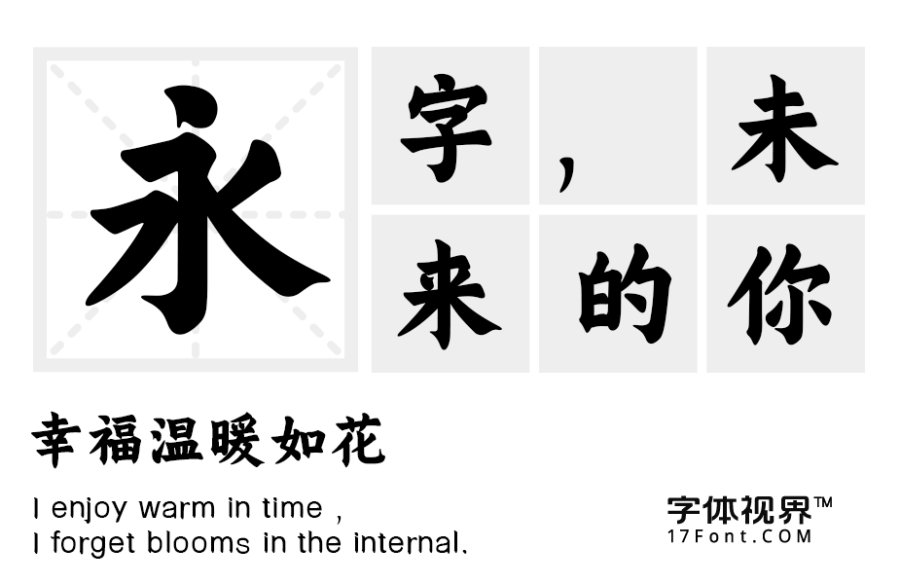
三极榜书简体发布
字体名称:三极榜书简体
字体类别: 书法字体
适用场景:标题、正文、印刷、屏显
三极榜书简体简介:三极榜书简体以传统楷书大字为结构雏形设计,笔画豪迈雄伟,笔墨中正,字形雍容大气,厚重沉稳,极富艺术感染力。适用于各类传统习俗的包装和宣传设计及书法作品排版标题、招牌设计。
三极榜书简体预览图展示: